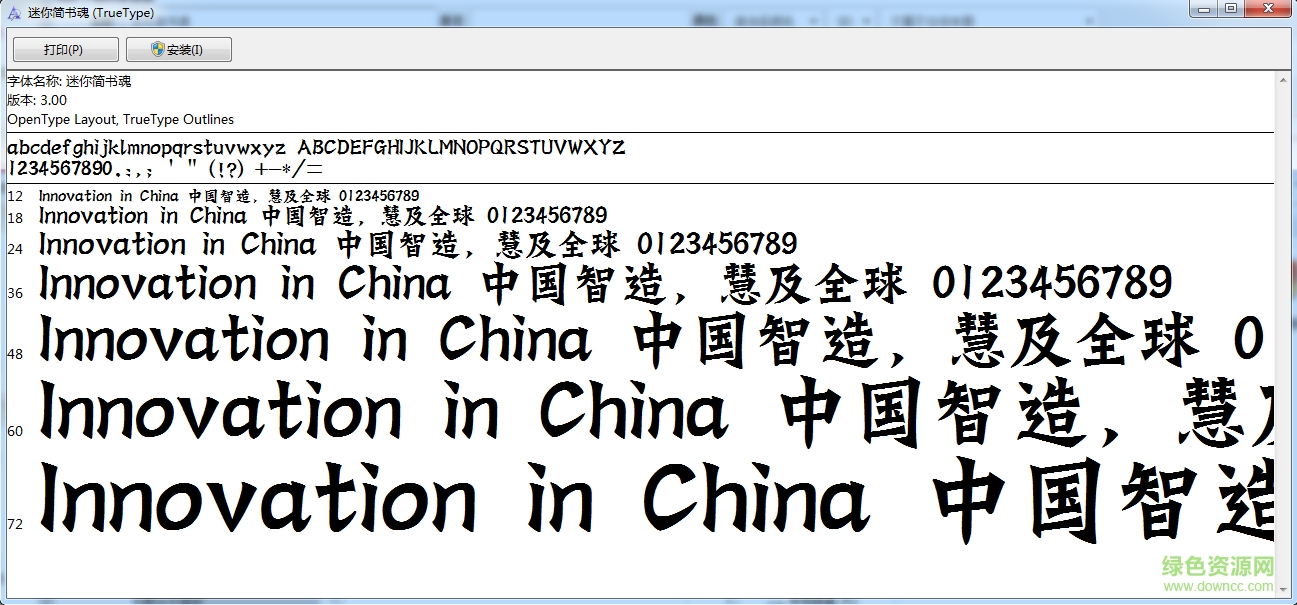
jsuhunti字體就是迷你簡書魂,該字體筆法豐富,內(nèi)斂外收,筆畫精致線條過渡平衡,醒目而富有韻味,可用與廣告設(shè)計、藝術(shù)設(shè)計、影視海報等方面,需要的朋友快來下載吧!
將魏碑的結(jié)體特點溶入印刷體中,并使之規(guī)整劃一,刀刻味十足。收筆方圓兼施,行筆輕重交錯!